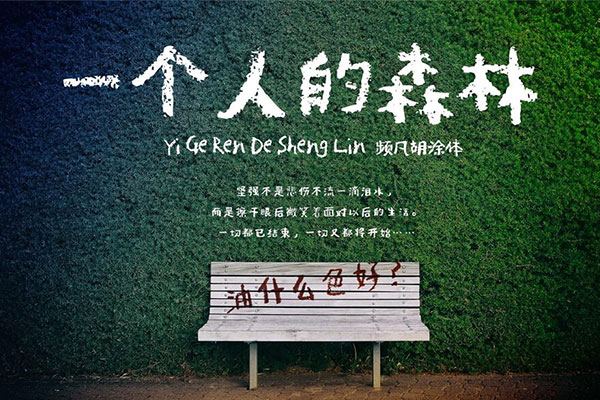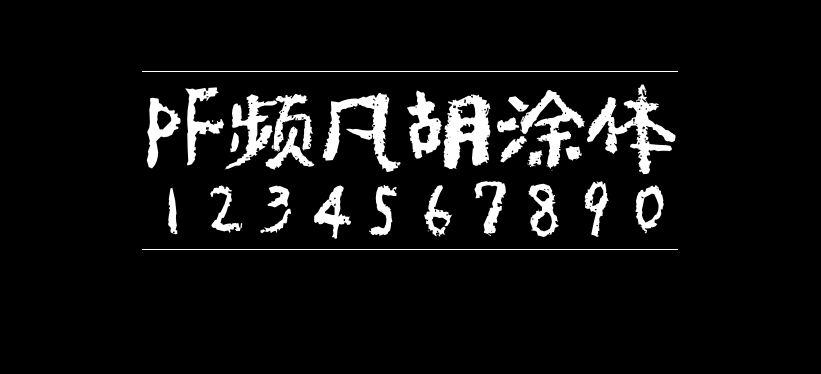
PF频凡胡涂体
PF频凡胡涂体(PFanHuTuTi)的作者是中国大陆的频凡™,该字体是基于一款日文粉笔风格字体增补而来的,弥补了中文免费粉笔风格字体的空白,但需要注意的是,该字体目前还在增补当中,简体和繁体均存在一定缺字现象。
以下是作者对该字体的介绍:
给儿子生日制作画面标题时,偶然发现一款日文字体,频凡感觉非常适合。奈何整体完成度较低,只含括二千余汉字,且多为日系繁体字形。字体应用后愈加喜欢,相遇即有缘,权当一份未来的生日礼物,遂产生增补冲动。
PF频凡胡涂体
字体命名来源于自己中年对“难得糊涂”的理解及字体涂鸦的本身。
字体风格:
这是一款手写字体,视觉上如同油漆/蜡笔在不平的表面涂抹,留下斑驳厚重的墨迹。粗糙中流露温柔,岁月感不显沧桑,纯手工赋予的文艺气质,推荐应用于动漫标题诗歌短文等场景。
增补目标:
一、支持简体中文编码——现代汉语常用字表(3500字),另按字频增加高频汉字及符号。
二、支持GB/T 2312 汉字表(6763字),满足中文简体需求;发布1.0简体正式版。
三、酌情补充常用繁体中文字符,满足国人中文简繁基础应用;发布2.0简繁正式版。
调整字形:
原字随性浪漫,字符大小不一,更有“逼真的笔迹感”;但因此使用性非常有限,字符堆叠难予辨认,尤其不适合文本。
基于设计感与阅读性的平衡,促进字体完成度,统一了字符宽高,逐字调整字符大小。同时,发现并修改原有日系字形,使其更加贴合简体中文规范和习惯。
发布计划:
字体因手写风格,笔划不同难以重复利用,导致补字难度加大,进展缓慢。目前时间松裕的情况下一天稳定扩增二十余字,即每月约600字;预计2023年初完成1.0简体正式版。
PF频凡胡涂体